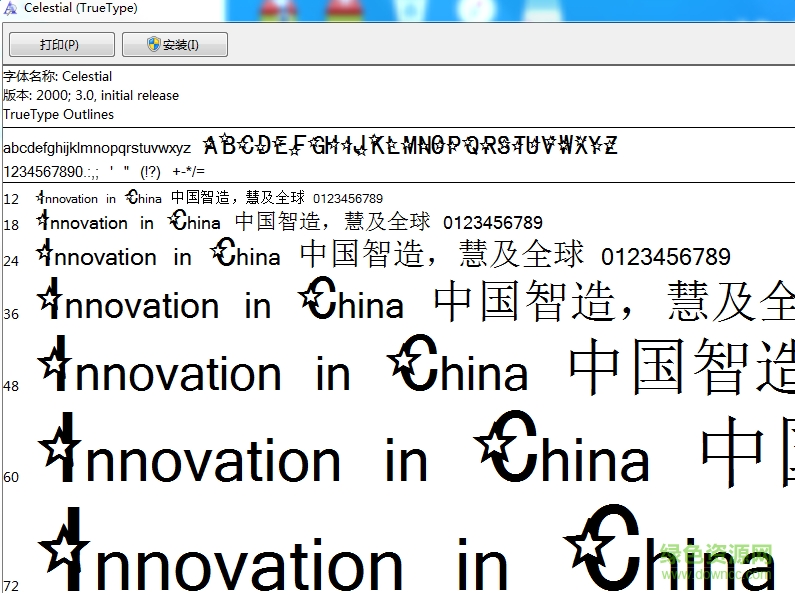
celestial字體是英文系列字體中很有個(gè)性的一種!本字體兼容多種系統(tǒng)環(huán)境,可以用來設(shè)計(jì)廣告、海報(bào)、兒童刊物使用!趕快來綠色資源網(wǎng)下載安裝吧。
Celestial字體是一款英文字體庫中的圓圈類英文字體,相信喜歡的用戶,不要錯(cuò)過哦!